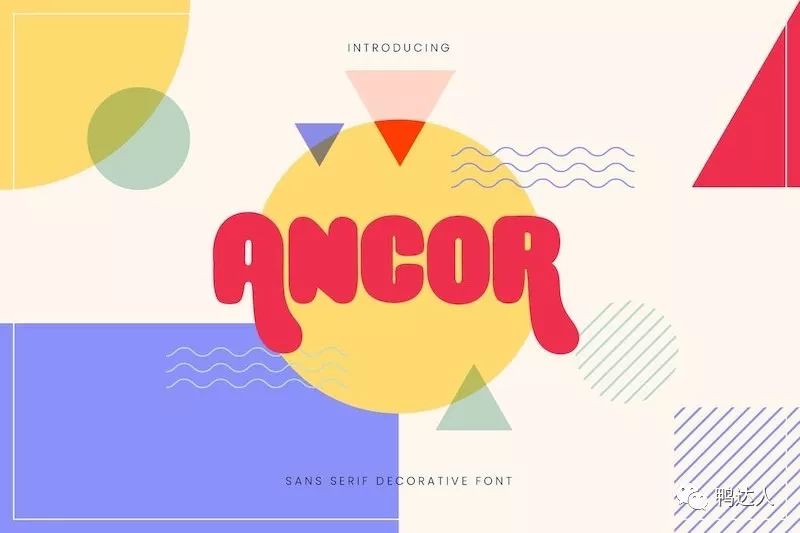
本期内容:孟菲斯风格的粗体无衬线英文字体Ancor
Ancor孟菲斯风格的粗体无衬线英文字体,所有字母都包含了大小写字母,以及符号和数字,该字体适用于休闲,活动,艺术,音乐和与儿童有关的设计项目。该字体素材包括了3种格式(otf,ttf,woff)procreate支持otf格式的字体导入哦~
(上面是鸭鸭用procreate做的字体插画,效果如图所示)